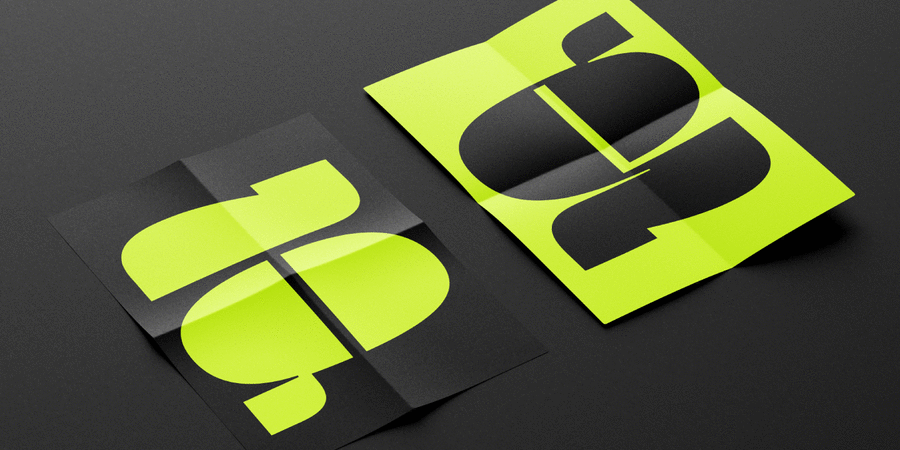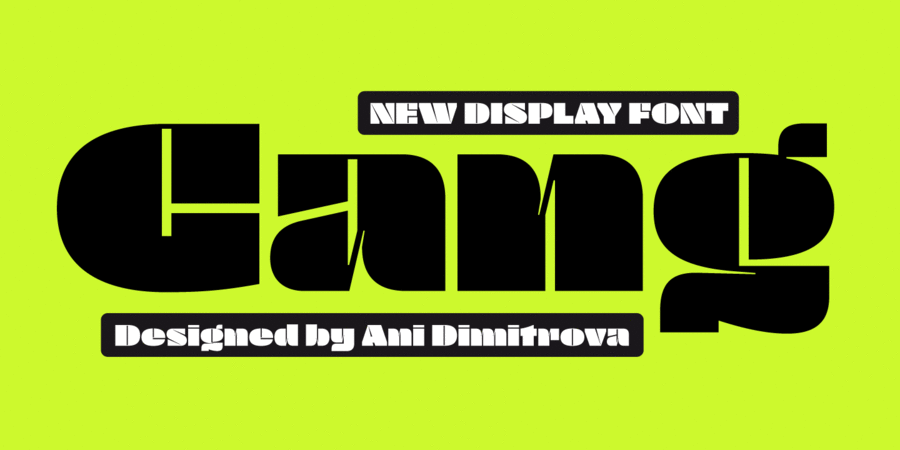
Gang (2 шрифта)
Опис гарнітури GangGang – це акцидентний шрифт із двома накресленнями, включно з трафаретним варіантом. Шрифт містить набір розширеної латинки та кирилиці, а також усілякі опентайп-фічі: стандартні лігатури, пропорційні цифри з відповідними знаками валют, індекси, стрілки та дроби. В обох накресленнях шрифт добре підходить для великих заголовків, виділення слів і різних видів реклами. Широкі пропорції роблять Gang ідеальним вибором для використання на екрані. Шрифт пропонує гнучкий діапазон для акцидентної типографіки. Ця гарнітура ідеально підходить для журналів, брендингу, плакатів, веб-дизайну та іншого. Шрифт розробила Ані Дімітрова в 2022 році.
Асоціації з сімейством шрифтів GangОсобистість і характер гарнітури:
переконливий, важкий, стійкий, сильний, самобутній, товстий, оригінальний, характерний, екстравагантний, химерний, помітний, яскравий, величезний, демонстративний, артистичний, виразний, твердий, дерев'яний, ремісничий, сміливий, різкий, претензійний, естетський, нонконформістський, експериментальний, активний, нахабний, чорний, іронічний, значний, сталевий, квадратний, мужній, впевнений, кондовий, суворий, індустріальний, рівний, чіткий, щільний, монументальний, залізний, амбітний, статичний, наполегливий, тісний, масивний, громіздкий, дивний, епатажний, крутий, потужний, дзвінкий, гучний, нав'язливий, важливий, екстремальний, мачо, ризикований, урбаністичний, вуличний, мотивуючий, зухвалий, грубий, жорсткий, брутальний, ігровий, міський, радикальний, прямокутний, солідний, стабільний, надійний, якісний, кінематографічний, запальний, робочий
фарба, розваги, реклама, інтер'єр, м'ясо, ремесло, кава, екскаватор, страйкбол, взуття, цегла, Місто, тренажери, атракціон, револьвер, інсектицид, гра, каскадер, екстрим, реп, концерт, шолом, супергерой, кіно, робочий, будівництво, інструмент, верстат, завод, металургія, порт, сейф, техніка, промисловість, охорона, захист, далекобійник, сталевар, залізниця Гарнітура асоціюється з віком: